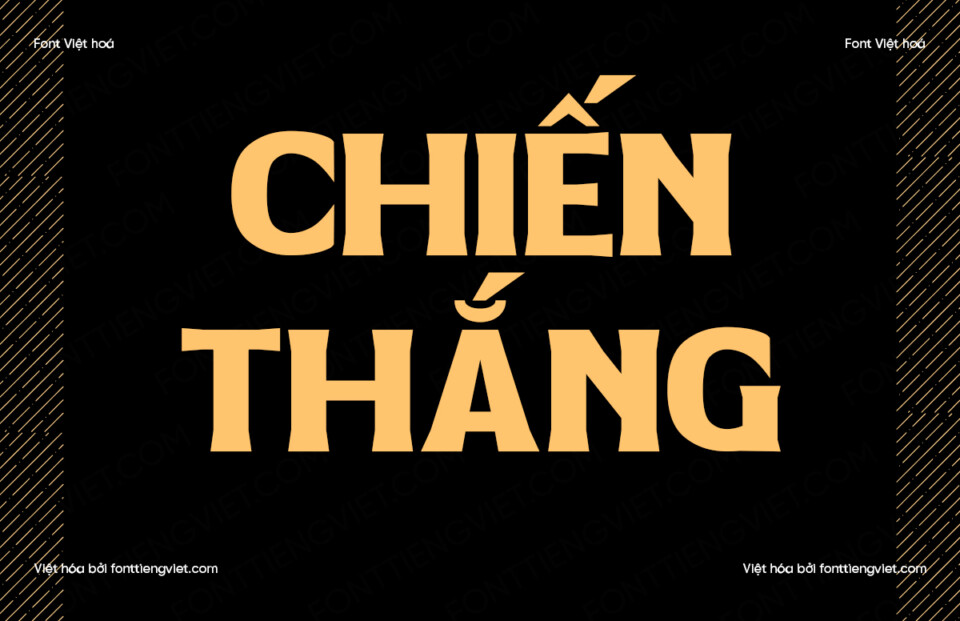
Font Việt hóa 1FTV VIP Goldener
Bộ Font Việt hóa 1FTV VIP Goldener Đẳng Cấp Sang Trọng Cho Thiết Kế
Trong thế giới đồ họa hiện đại, việc lựa chọn một bộ phông chữ phù hợp đóng vai trò quyết định đến linh hồn của tác phẩm. Font Việt hóa 1FTV VIP Goldener nổi lên như một hiện tượng trong cộng đồng thiết kế Việt Nam nhờ sự kết hợp hoàn mỹ giữa nét cổ điển và hơi thở đương đại. Nếu bạn đang tìm kiếm một công cụ hỗ trợ đắc lực để nâng tầm thương hiệu hoặc tạo ra những ấn phẩm truyền thông chuyên nghiệp, thì việc khám phá Font Miễn Phí chính là bước đi đầu tiên vô cùng đúng đắn. Bài viết này sẽ giúp các bạn học sinh, sinh viên và những người yêu đồ họa hiểu rõ hơn về giá trị nghệ thuật mà bộ font này mang lại cho người dùng Việt.
Đặc điểm nổi bật của Font Việt hóa 1FTV VIP Goldener
Bộ Font Việt hóa 1FTV VIP Goldener không chỉ đơn thuần là các ký tự chữ cái, mà nó còn là một tác phẩm nghệ thuật được chăm chút tỉ mỉ. Với các đường nét thanh mảnh đan xen cùng những điểm nhấn đậm chắc chắn, bộ font này tạo nên cảm giác uyển chuyển nhưng không kém phần quyền lực. Đặc biệt, quá trình Việt hóa đã được thực hiện cực kỳ công phu, đảm bảo tất cả các dấu tiếng Việt đều được đặt đúng vị trí, không bị lỗi hiển thị hay mất nét – một vấn đề mà nhiều người thường gặp phải khi sử dụng các phông chữ nước ngoài chưa qua xử lý.
Tính ứng dụng cao trong thiết kế thực tế
Nhờ vẻ ngoài sang trọng, Font Việt hóa 1FTV VIP Goldener thường xuyên được các nhà thiết kế ưu ái sử dụng trong các dự án cao cấp. Bạn có thể dễ dàng bắt gặp bộ font này trên các tấm thiệp mời đám cưới trang trọng, bìa sách nghệ thuật hoặc các ấn phẩm quảng cáo cho các nhãn hàng thời trang, mỹ phẩm. Đối với các bạn học sinh đang làm báo tường hay thiết kế slide thuyết trình, việc sử dụng bộ chữ này sẽ giúp bài làm trở nên thu hút và chuyên nghiệp hơn rất nhiều trong mắt thầy cô và bạn bè.
Tại sao nên lựa chọn Font Việt hóa 1FTV VIP Goldener?
Lý do đầu tiên khiến bộ font này được yêu thích chính là khả năng tương thích tuyệt vời trên nhiều phần mềm thiết kế phổ biến hiện nay như Photoshop, Illustrator, hay thậm chí là các ứng dụng đơn giản trên điện thoại như Canva và PicsArt. Điều này giúp người dùng tiết kiệm được rất nhiều thời gian trong khâu chỉnh sửa kỹ thuật. Bên cạnh đó, phong cách “Goldener” mang lại một cảm giác ấm áp, quý phái, giúp khơi gợi cảm xúc tích cực cho người xem ngay từ cái nhìn đầu tiên.
Lưu ý khi sử dụng bộ font trong bài thiết kế
Dù Font Việt hóa 1FTV VIP Goldener rất đẹp, nhưng để đạt hiệu quả thẩm mỹ cao nhất, người dùng nên chú ý đến cách phối hợp màu sắc. Vì tên gọi mang xu hướng “vàng kim”, bạn nên kết hợp font này với các tông màu nền trầm như đen, xanh navy hoặc đỏ đô để làm nổi bật các đường nét tinh tế. Đừng quên căn chỉnh khoảng cách giữa các chữ cái (kerning) sao cho hợp lý để văn bản của bạn trông hài hòa và dễ đọc nhất có thể.